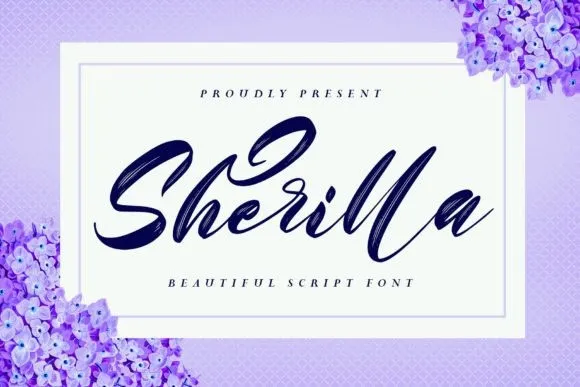
Sherilla Font – Download Grátis
A Sherilla Font é uma opção perfeita para quem busca um estilo elegante e moderno no seu design visual. Com um texto frondoso e detalhado na textura de pincel, ela oferece uma aparência sofisticada que encaixa-se em diversos tipos de projetos gráficos. Esta fonte tem sido criada pelo designer Nox Studio para ser usada não apenas nas letras dos logos ou identidades visuais, mas também para rótulos, embalagens, convites e decorações de festa, desde os anúncios até as postagens no Instagram. O PUA encoding da fonte torna-a extremamente funcional, permitindo a facilidade na utilização completa dos caracteres e das curvas chamadas swashes, proporcionando flexibilidade para um amplo leque de aplicativos criativos. É uma escolha perfeita para quem valoriza tanto o design elegante quanto as possibilidades inovadoras oferecidas por essa font.